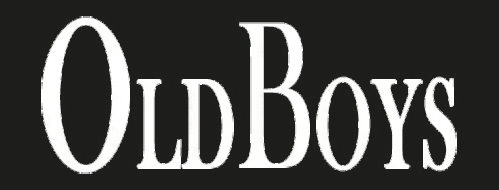
Suche Schriftart von "OLDBOYS"
kennt jemand die Schriftart vom Schriftzug "OLDBOYS".
Ich habe dazu leider keine weiteren Infos...
Etwas ähnliches reicht auch.
In der Breite auf 50 % gestaucht.